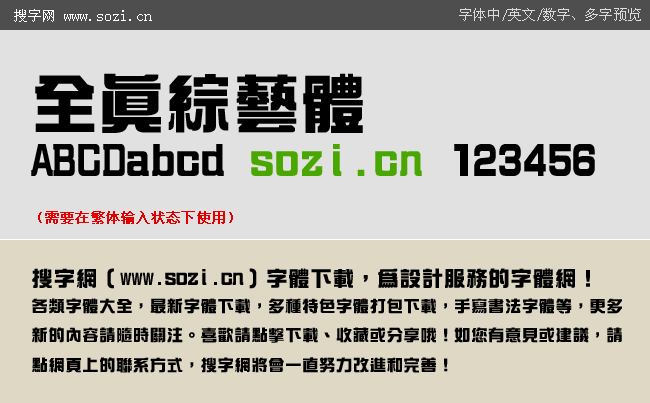
全真中綜藝體
搜字網(wǎng)提供一款全真中綜藝體下載。此款字體為繁體字體,綜藝體是黑體的一種變體,也是藝術(shù)字的一種。特點(diǎn)是筆劃更粗,盡量將空間充滿。同時(shí)為了美觀,對拐彎處的處理較為圓潤。適用于廣告、報(bào)刊等的標(biāo)題及海報(bào)展板等設(shè)計(jì)場合使用。